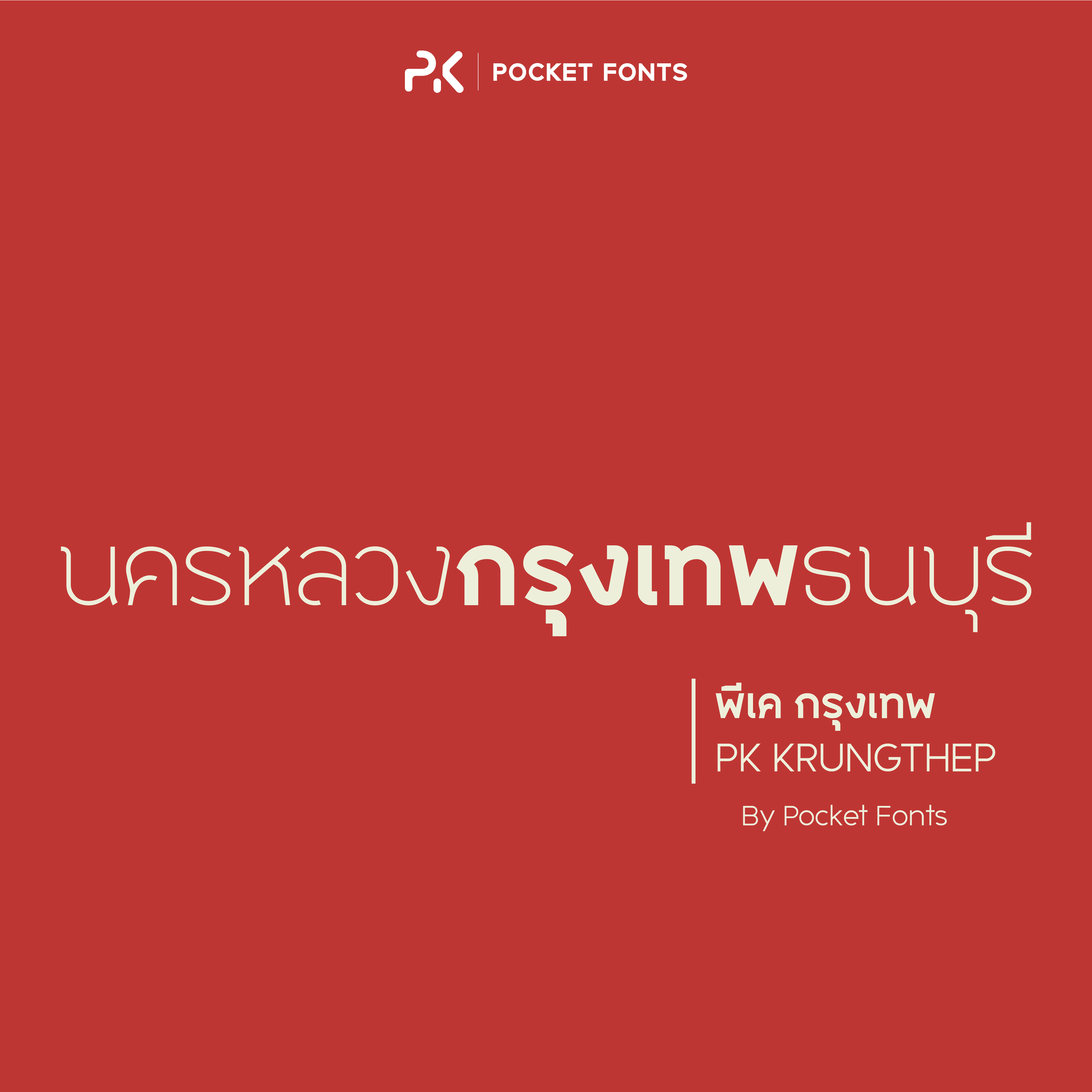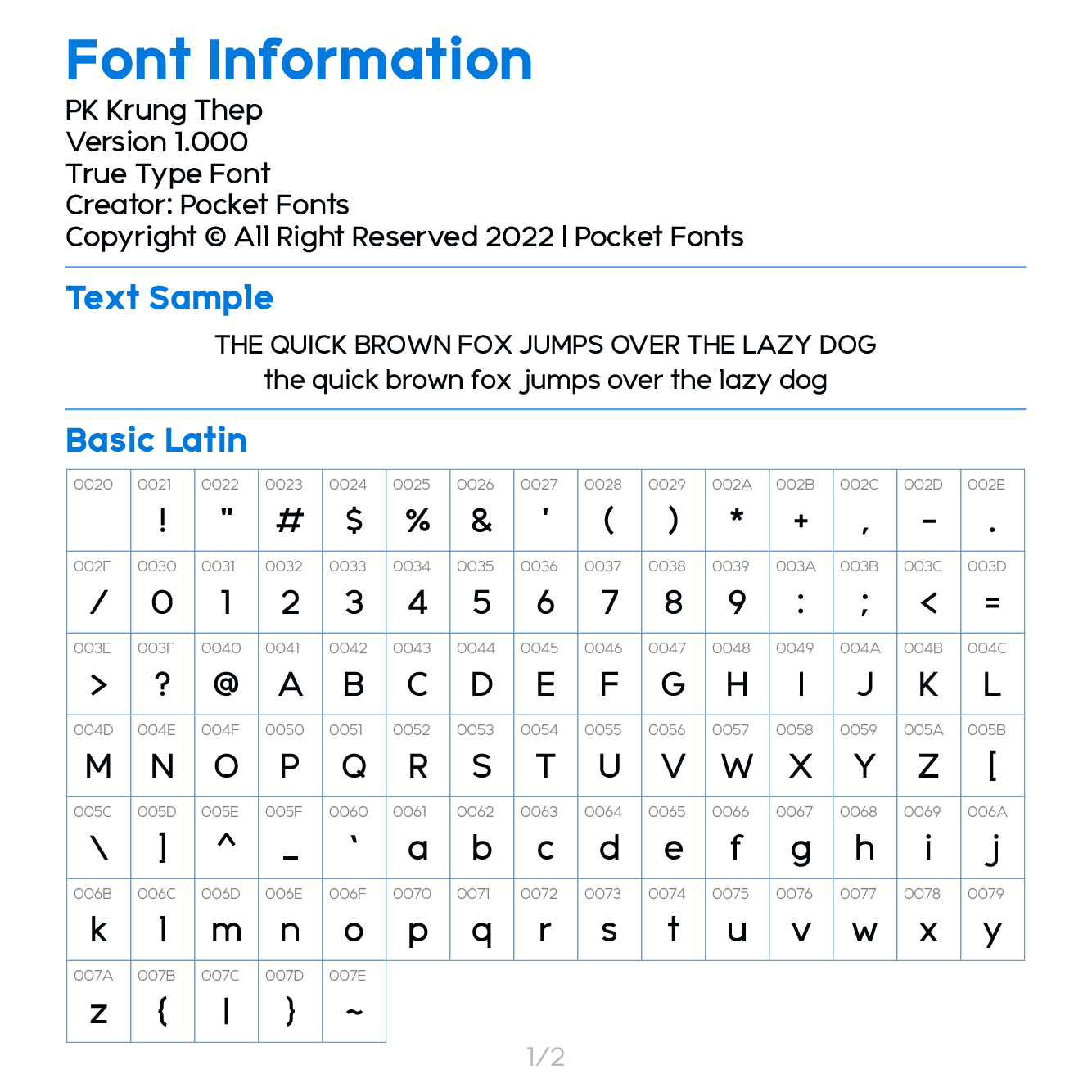
PK Krung Thep
ชื่อฟอนต์ : พีเค กรุงเทพ | PK Krung Thep
ฟอนต์ พีเค กรุงเทพ (PK Krung Thep) เป็นฟอนต์สไตล์โมเดิร์น ดีไซน์โค้งมน ดูเรียบง่าย ทันสมัย สะอาดตา อ่านง่าย มีด้วยกัน 7 น้ำหนัก และเป็น Variable font สามารถปรับน้ำหนักแบบ Custom ได้